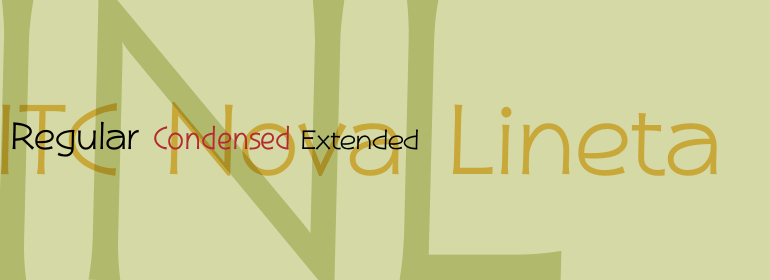
ITC Nova Lineta™
ITC Nova Lineta™,这款字体结构工整、笔画清晰,兼顾美观与易读性,适用于标题、正文、海报、包装、LOGO 等多种场景。字形优雅稳定,风格百搭耐看,适配日常排版与创意设计,让文字呈现更舒适、更具质感。ITC Nova Lineta™一笔一画,皆是细节,以均衡的比例、流畅的线条打造舒适视觉体验,字形端正大气,风格简约现代。无论是商业设计、品牌宣传还是日常排版,都能轻松驾驭,让文字更有格调与力量。ITC Nova Lineta™字体下载。
字体品牌: ITC(Monotype) 设计师:Jelesijevic,Slobodan 字体分类:衬线体 字体属性:外文 字符集:Unicode 发布时间: 2018